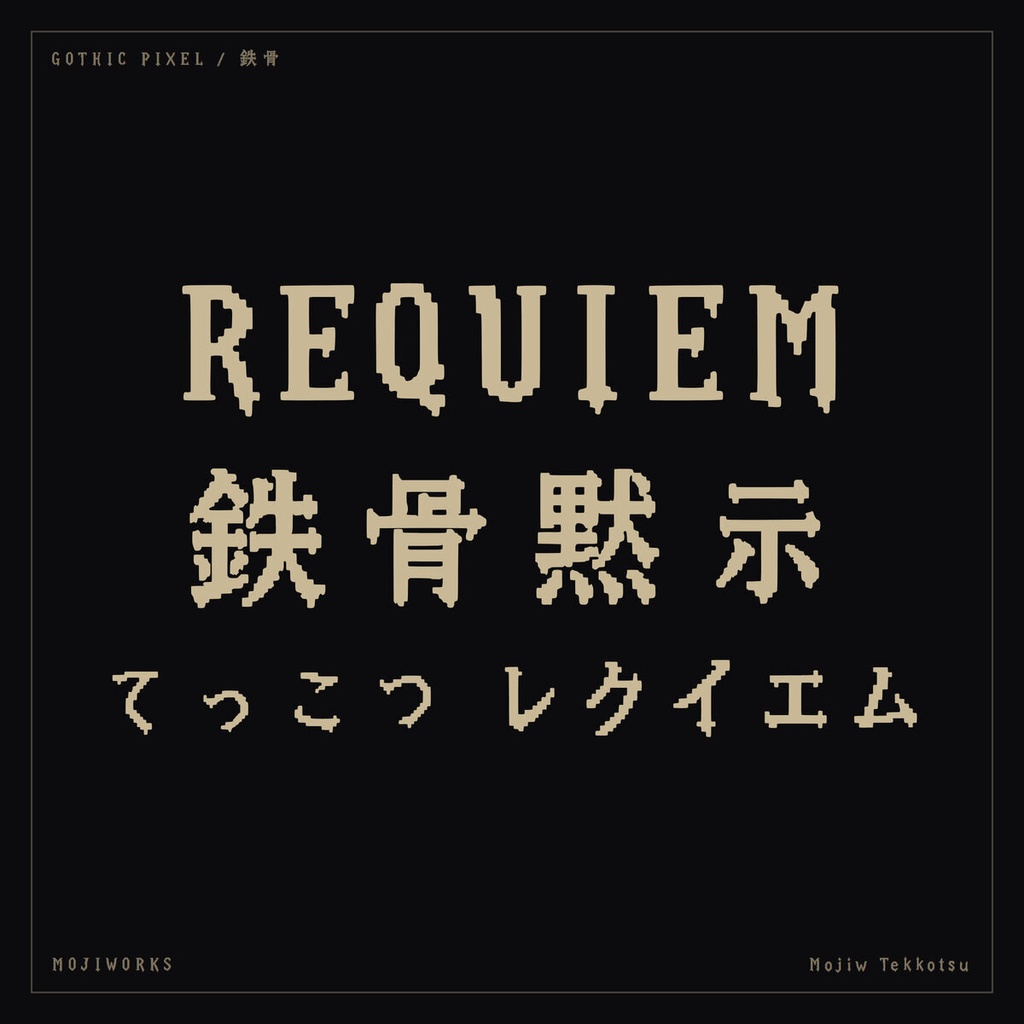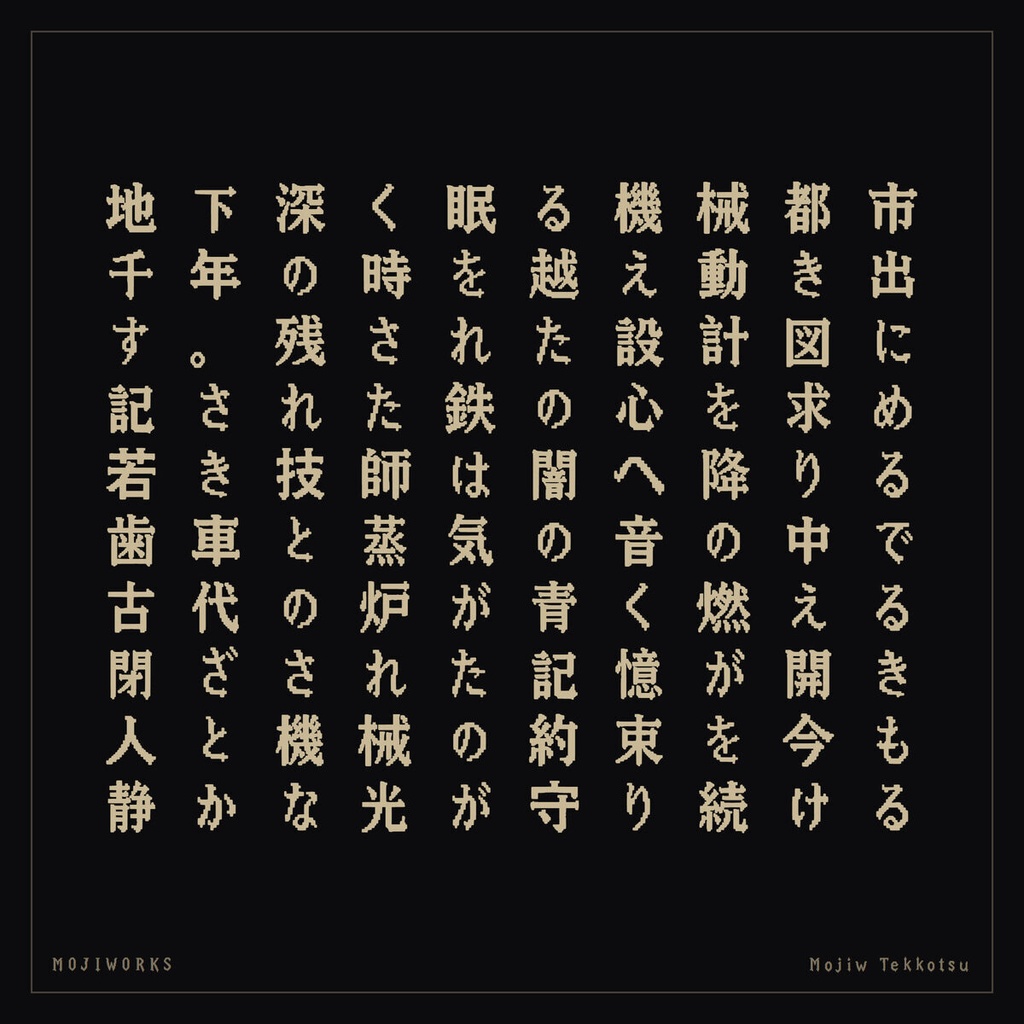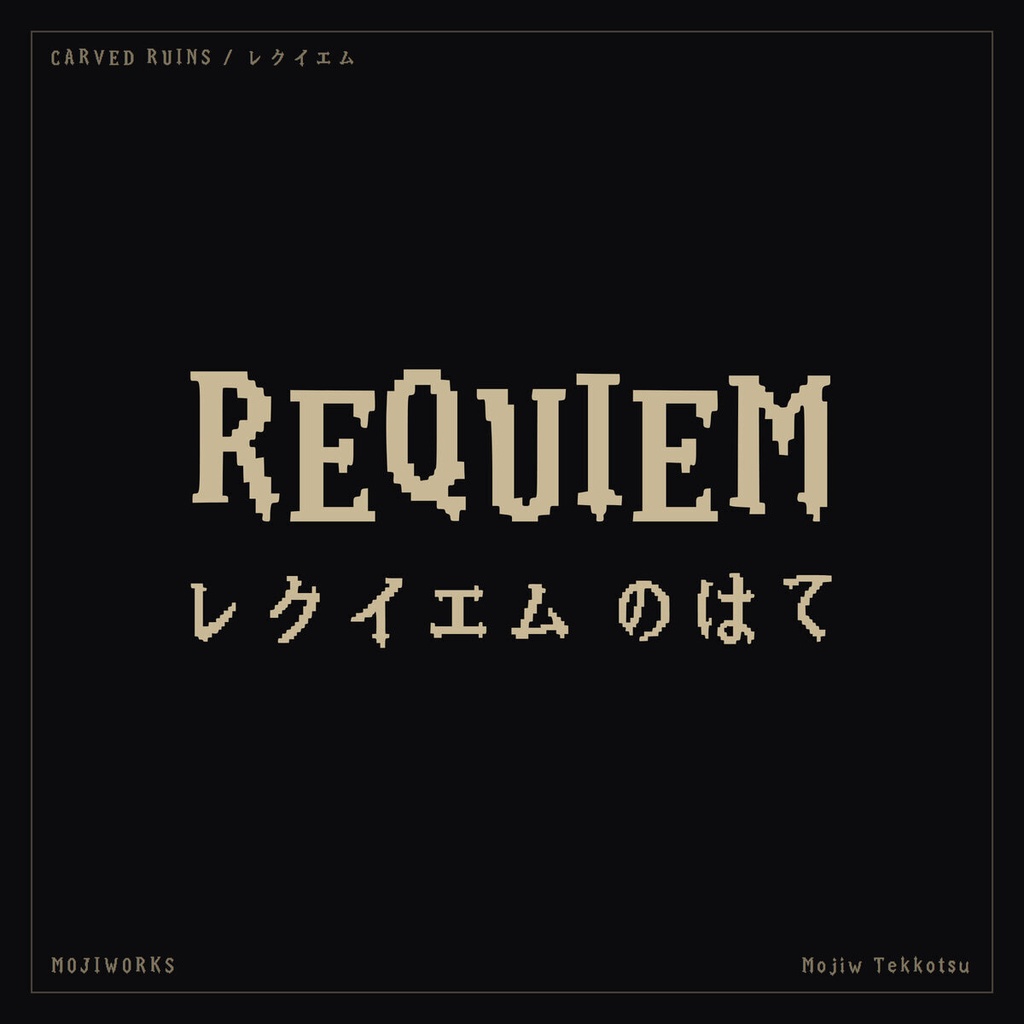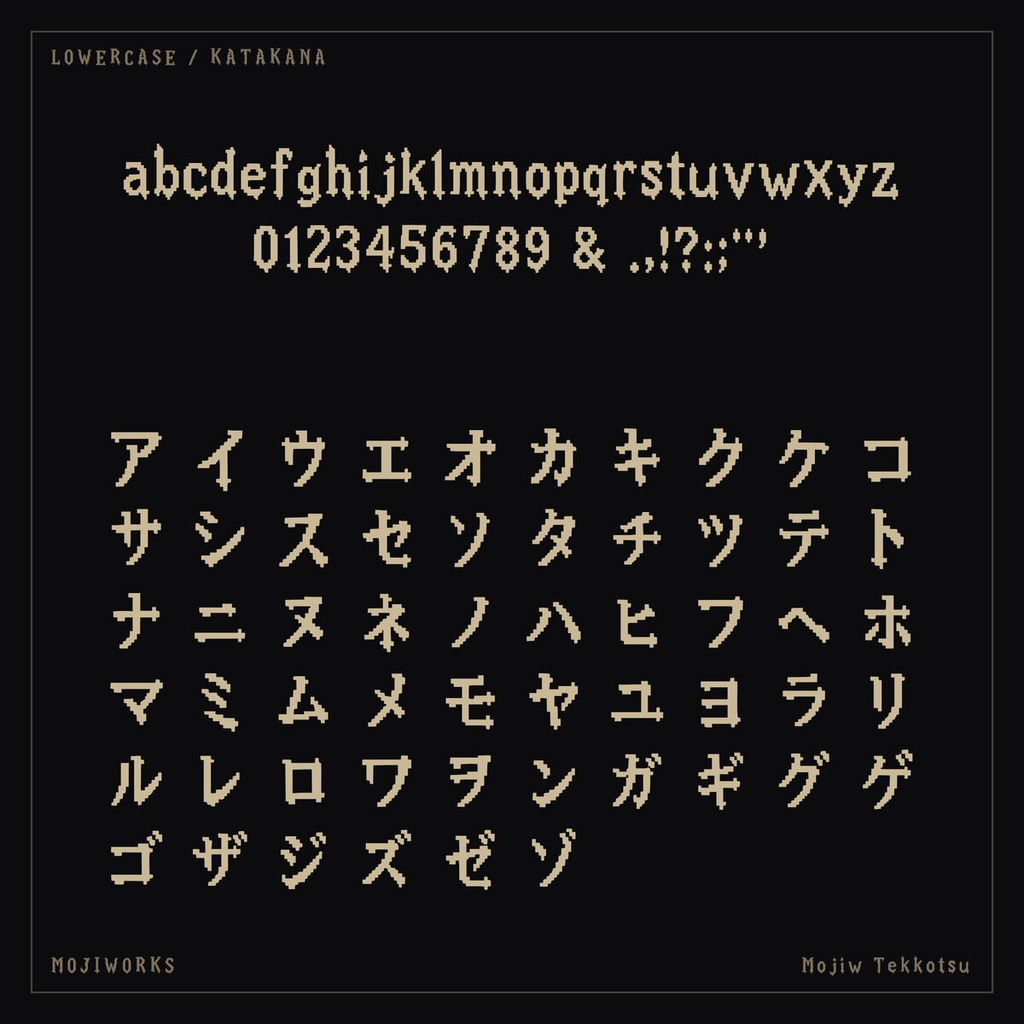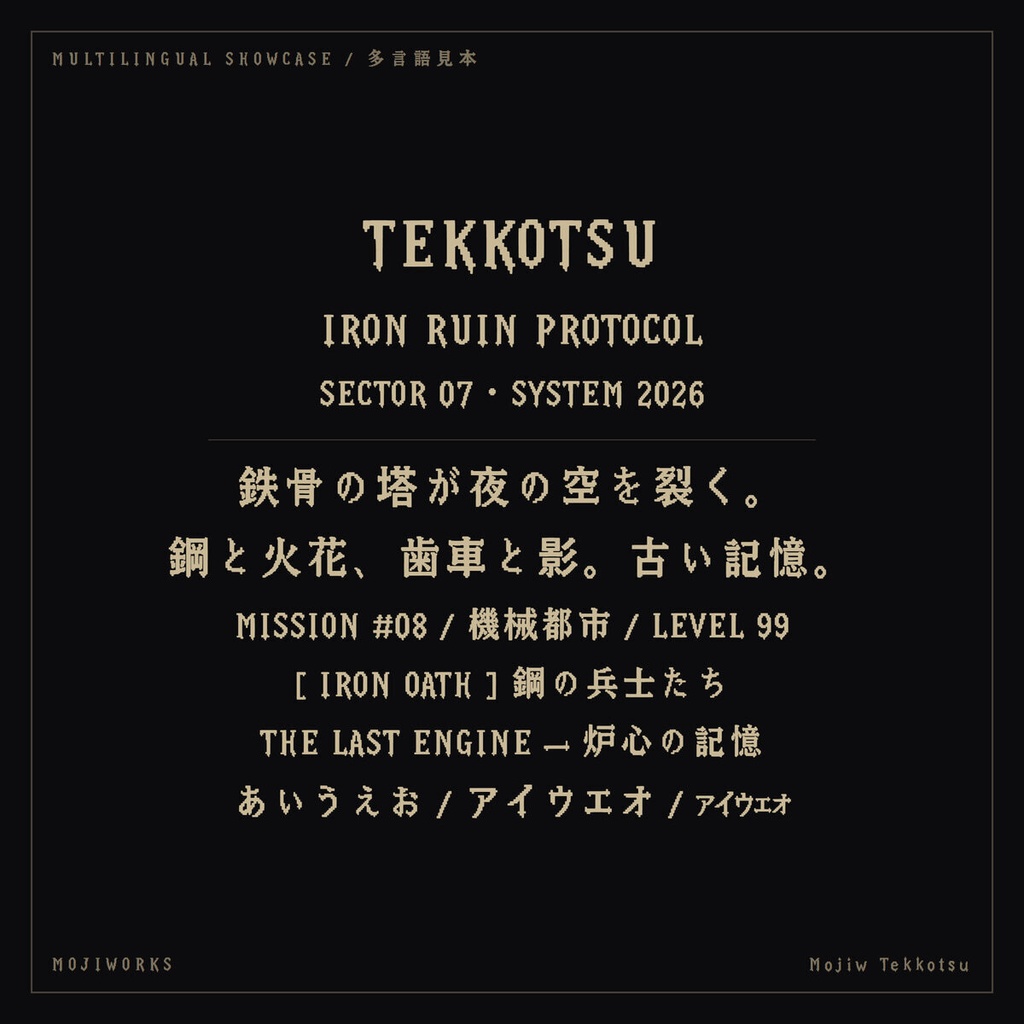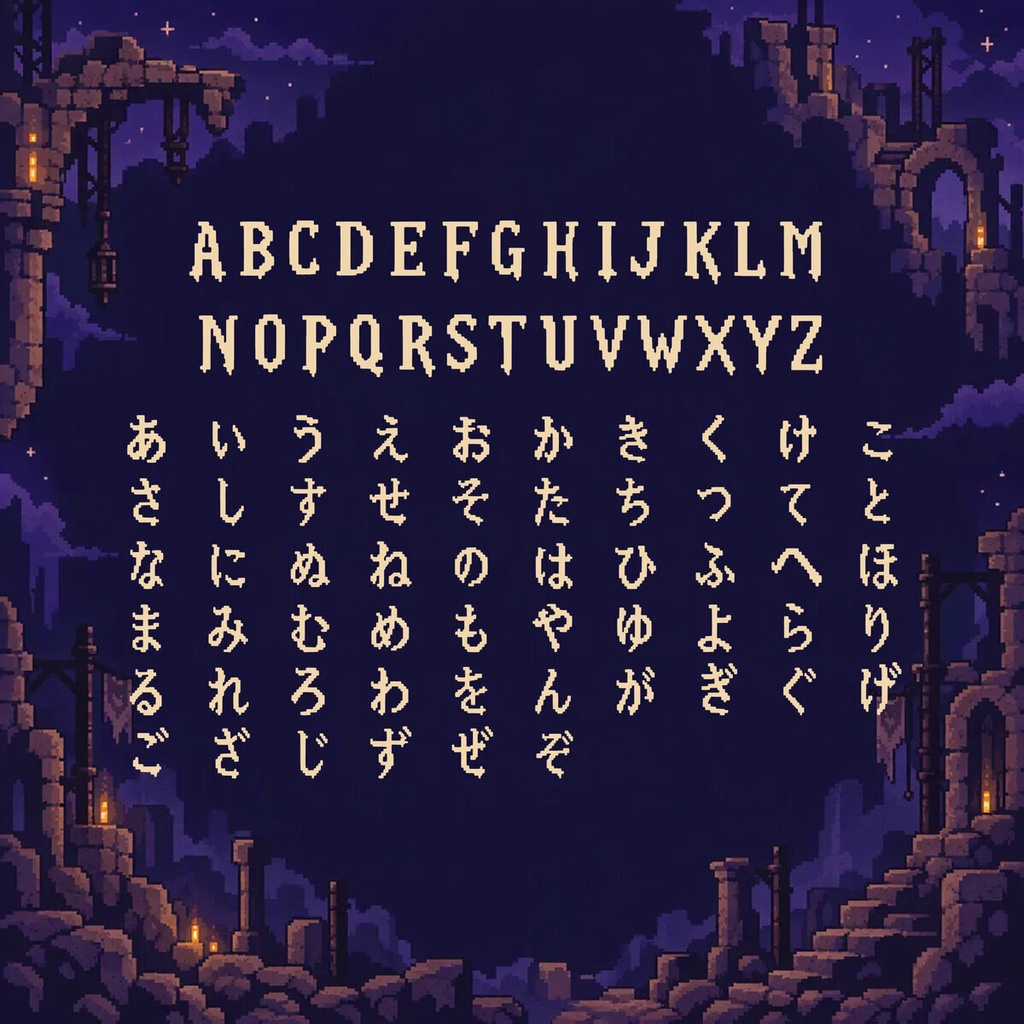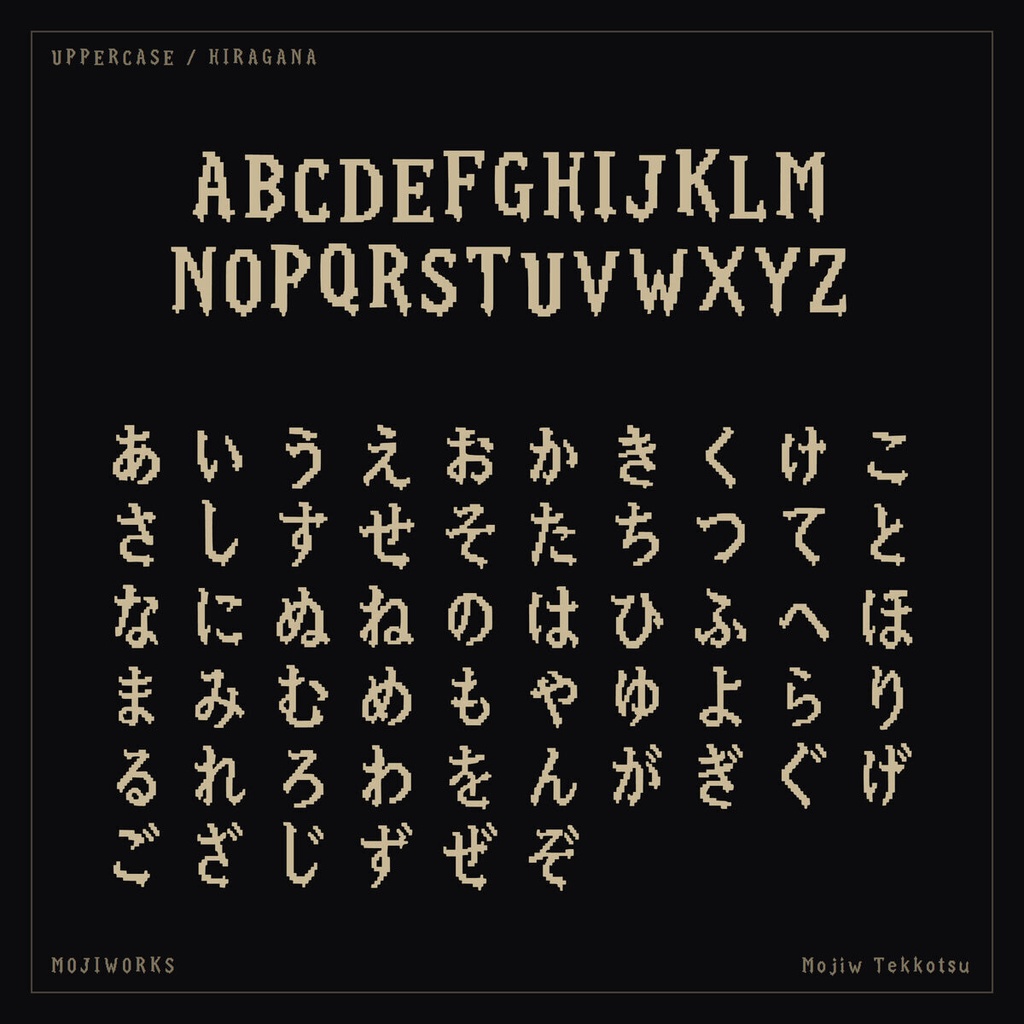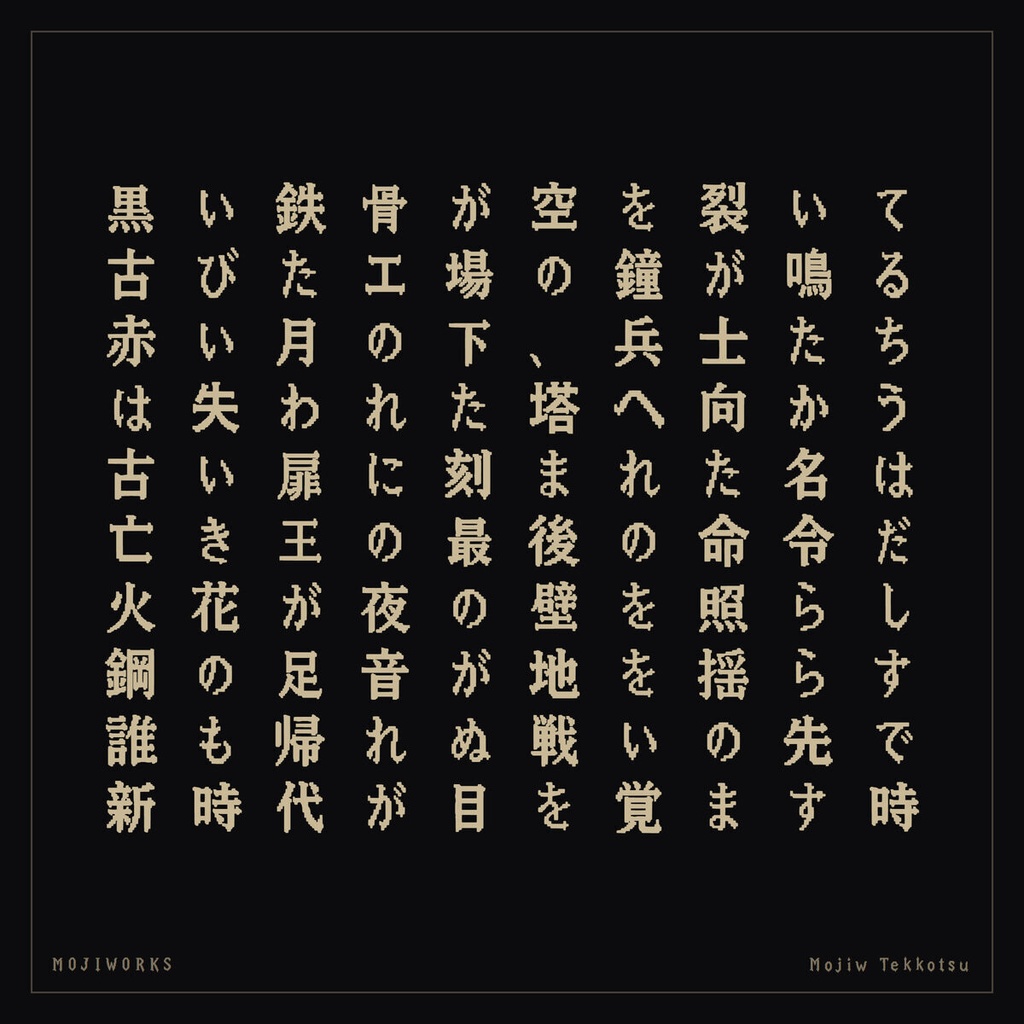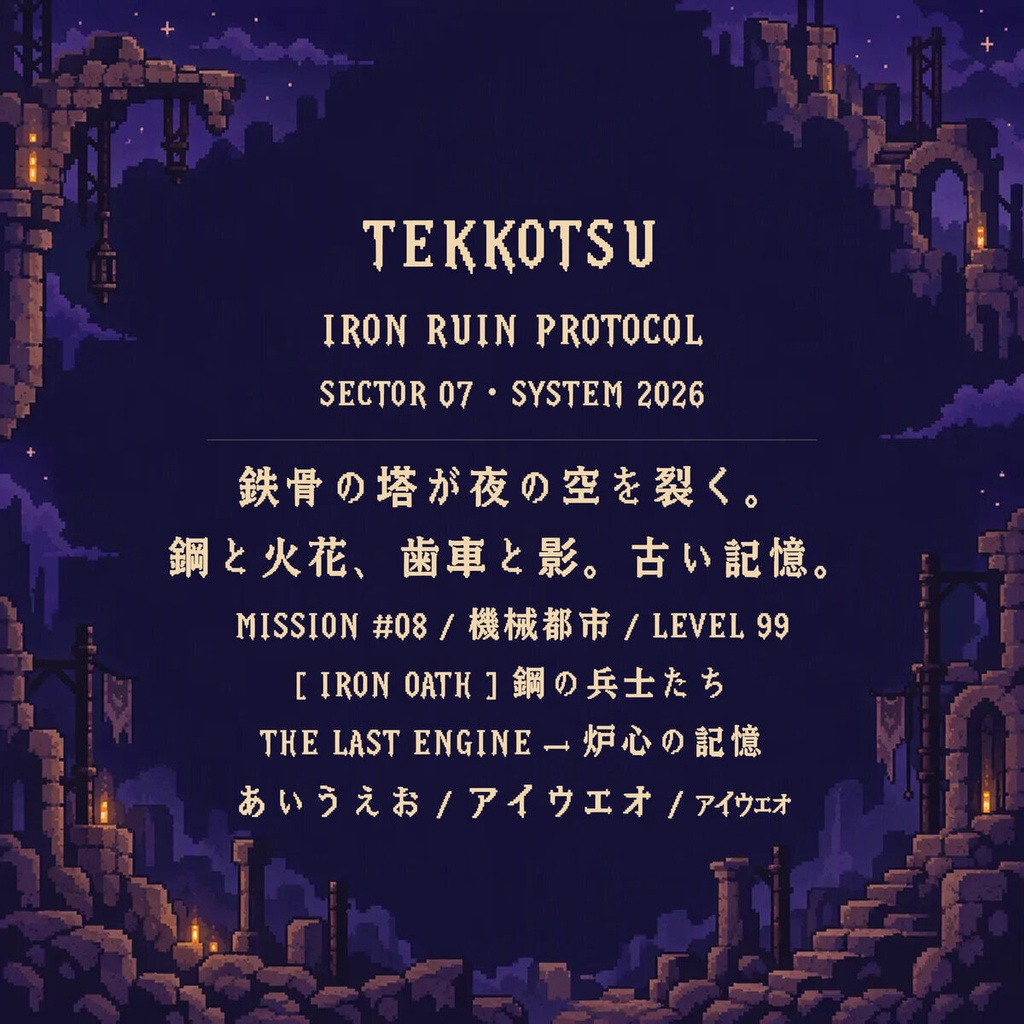
鉄骨 Tekkotsu【フォント】 — 鋼鉄級ヘビーディスプレイ|常用漢字2,136字
鉄骨のように鋭く重い、ゴシックピクセル書体です。 A sharp, heavy gothic-pixel display face forged like an iron frame. 【用途 / Use】 ダークファンタジー / メトロイドヴァニア / ゲームUI / ロゴ / MV For dark fantasy, metroidvanias, game UI, logos, and music videos. 【常用漢字フル版 / Joyo Complete】 常用漢字2,136字を完全収録し、ラテン文字・ひらがな・カタカナ・記号を含む全2,437文字を収録しています。半角カナは収録していません。 Includes all 2,136 Joyo kanji and 2,437 characters total, including Latin, hiragana, katakana, and punctuation. Half-width kana are not included. 2437文字 / characters 【関連する収録版 / Other Edition】 ラテン文字・かな・記号を収録したスタンダード版もあります。 The Standard edition includes Latin, kana, and punctuation. ▶ スタンダード版 / Standard: https://mojiworks.booth.pm/items/8826760 【フォント仕様 / Specification】 バージョン / Version: 1.1.1 形式 / Format: TrueType (.ttf), Web (.woff2) 対応環境 / Platform: Windows, macOS, web browsers 収録字一覧 / Character list: CHARSET.txt 同梱 / Included: font files, README, LICENSE, character list, portfolio PDF, product previews. 【利用規約 / License Summary】 個人・商用利用可。1ライセンスは購入者1名に適用されます。 Personal and commercial use is permitted. One license covers one purchaser. 印刷・動画・ロゴ・グッズ等の静的成果物、および購入者が運営するサイトでの同梱WOFF2の利用が可能です。 Static output such as print, video, logos, and merchandise is permitted. The bundled WOFF2 may be used on a website owned or operated by the purchaser. ゲーム・アプリへの組み込みは、利用者が生のフォントを抽出できない形式に限ります。生のフォントを同梱する場合は別途ライセンスをご相談ください。 Game/app embedding requires protection against extraction of the raw font. Contact us for a separate runtime-embedding license when shipping raw font files. 標準ライセンスは1製品・1サイトあたり年間約100,000ユーザーまで。従業員50名超の組織を含む大規模利用は要相談。 Standard coverage is approximately 100,000 users per product/site/year. Larger use and organizations with more than 50 employees require an extended license. フォント本体の再配布・販売・貸与・変換・グリフ抽出・派生フォント制作・生成AI学習やスタイル参照は禁止です。 Redistribution, resale, lending, conversion, glyph extraction, derivative fonts, and generative-AI training or style reference are prohibited. 完全な利用条件は同梱の LICENSE.txt / LICENSE.jp.txt をご確認ください。 The bundled license files are authoritative; consult them for the complete terms. 【ほかのフォント・カスタム制作 / More Fonts and Custom Work】 フォント一覧、オーダーメイド書体、文字追加、拡張ライセンスのご相談はこちら。 Browse our catalog or contact us for custom typefaces, added characters, and extended licenses. https://mojiworks.booth.pm/